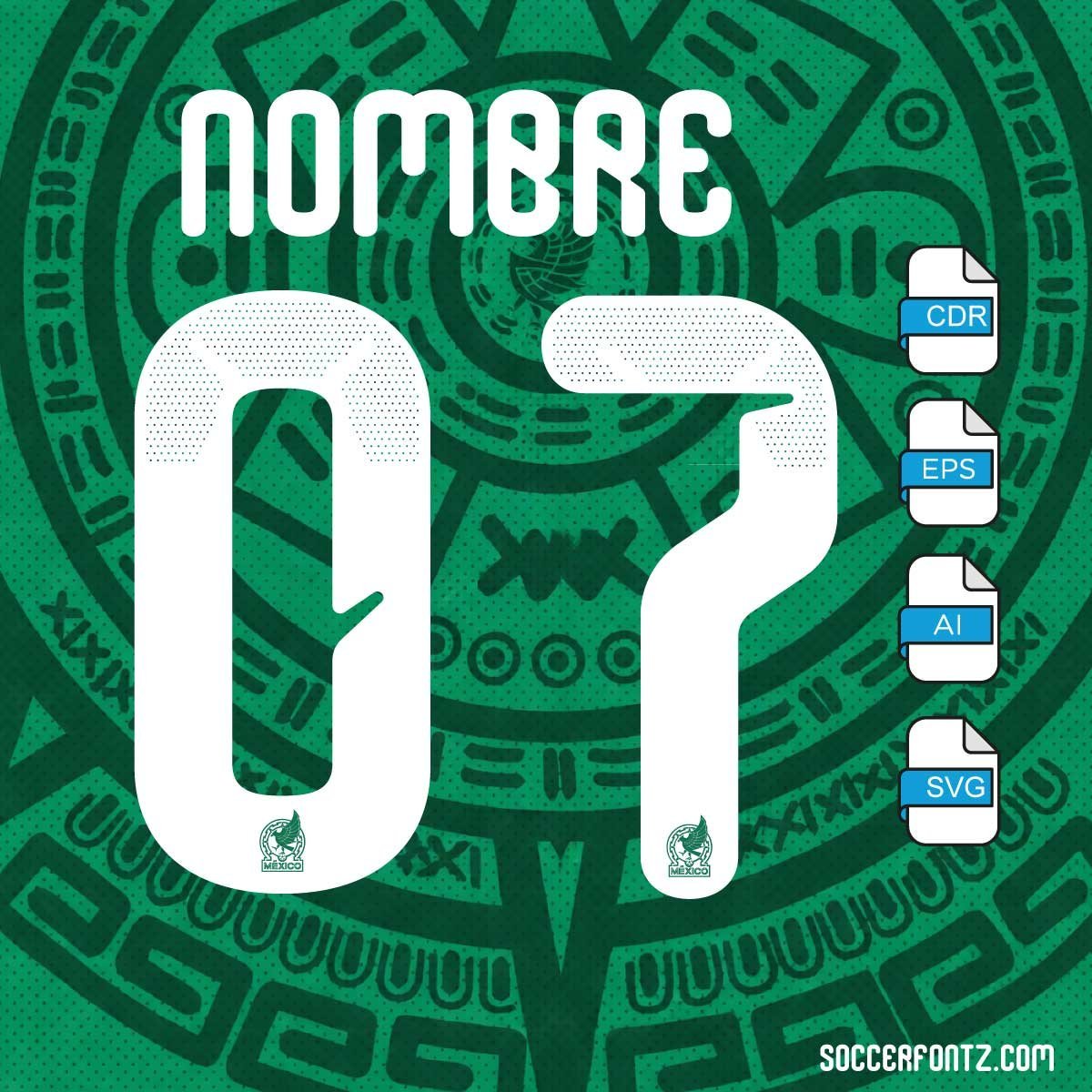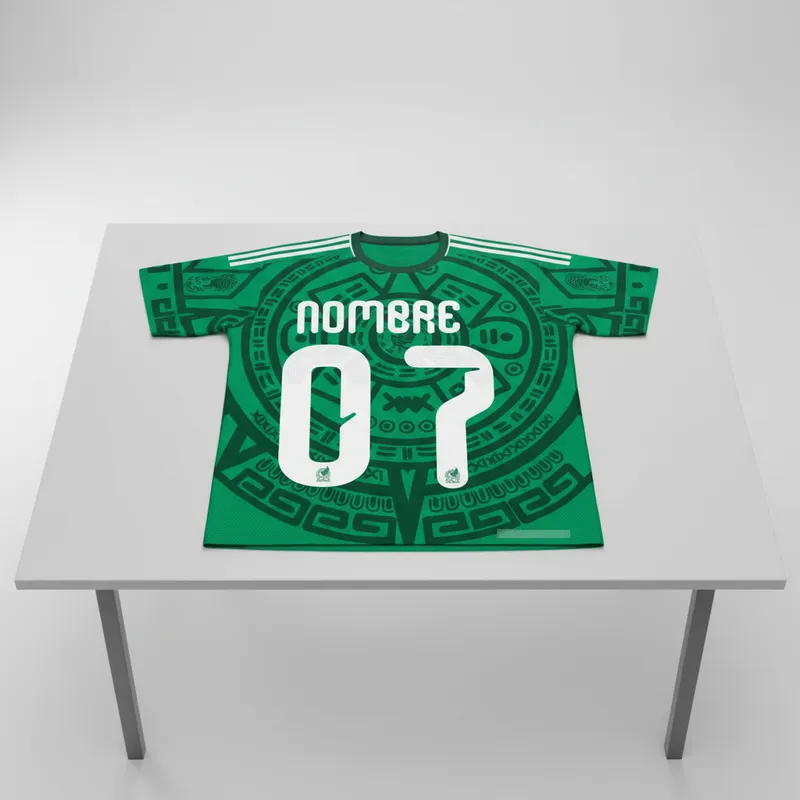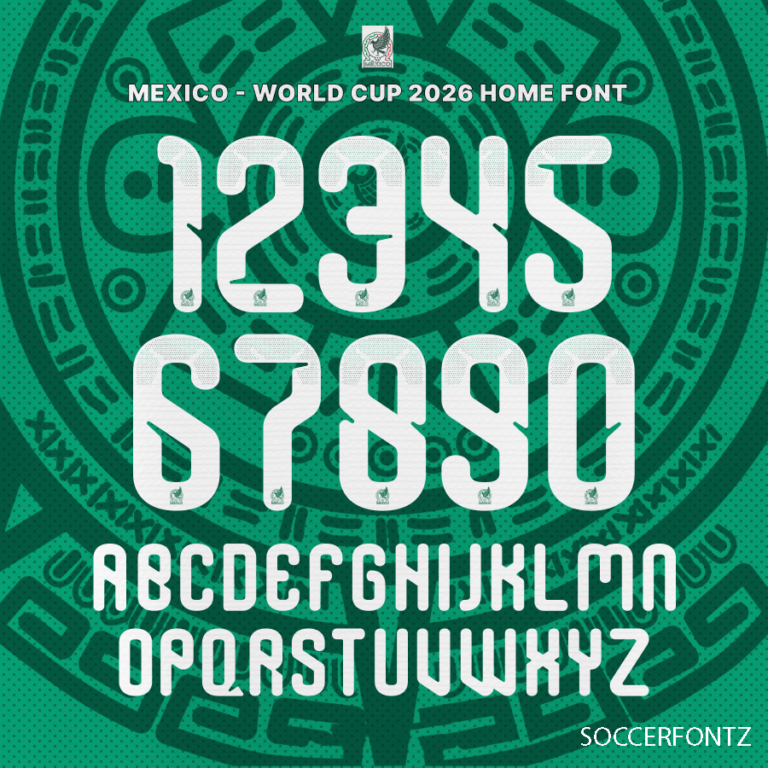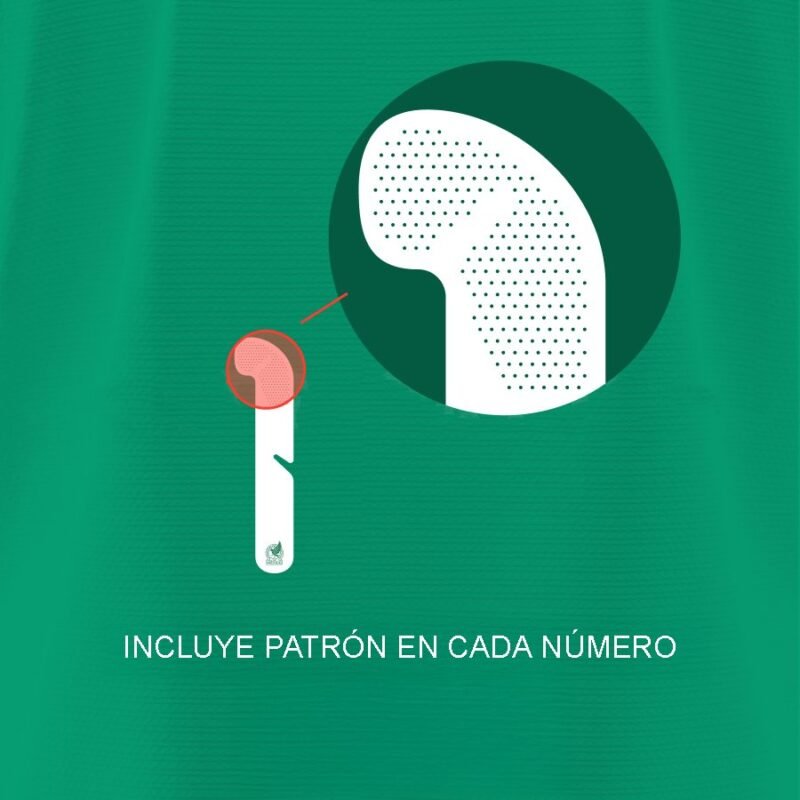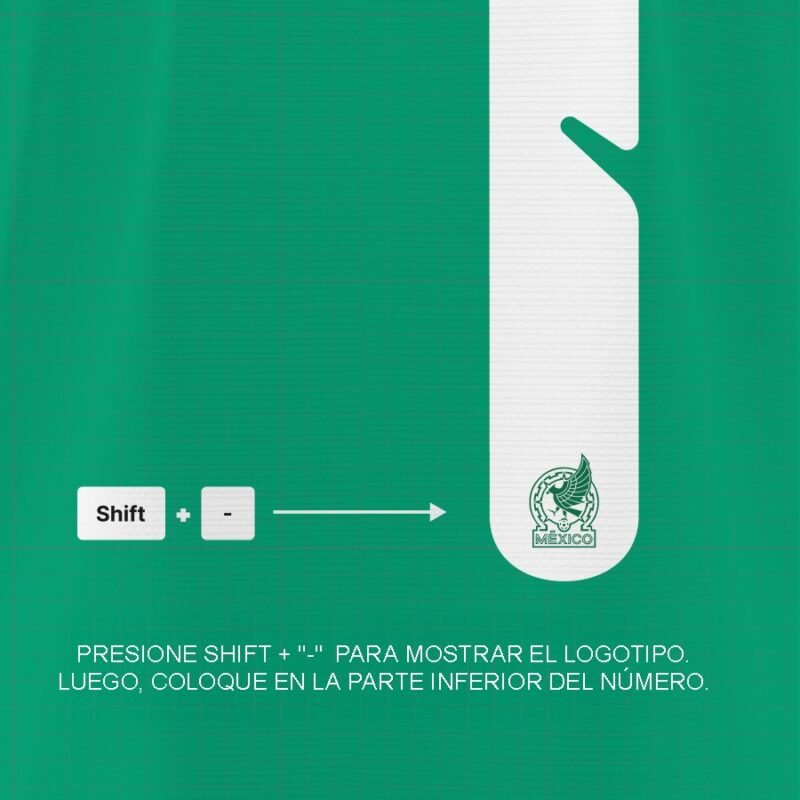
TIPOGRAFÍA MÉXICO – MUNDIAL 2026
Ideal para corte en vinil
Resultados limpios y profesionales.
Uso flexible
Apta para vinil, sublimación, impresión y más.
Detalles que hacen única esta tipografía
Incluye patrón en cada número
Cada número cuenta con un patrón integrado que aporta identidad, textura y un look profesional en playeras y diseños deportivos.
Shift + tecla "-"
Incluye un elemento gráfico inspirado en la identidad nacional que puedes activar fácilmente desde el teclado y colocar en tus diseños.
Glifo de la cresta nacional para mayor autenticidad
Números 0-9 y alfabeto en mayúsculas completo A-Z
Incluye glifo del logotipo de la cresta para un detalle 100% auténtico